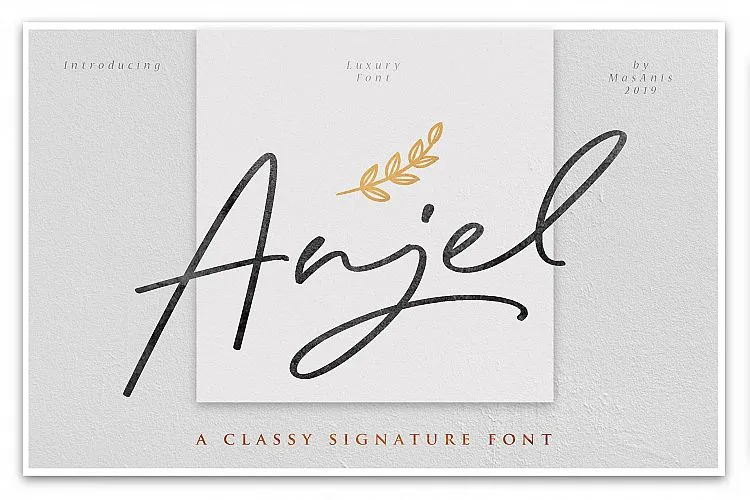
Este é um novo tipo de script autografado para anúncios de alta qualidade, com uma sensação sofisticada que certamente complementará seu próximo projeto. Introduzimos a Anjel Font. Esta foi criada e compartilhada por Mas Anis, o designer criativo do tipo de letra Anjel Signature. Este é um famoso anúncio digitado à mão cuja linguagem inclui minúsculas, maiúsculas, símbolos e suporta várias línguas. Além disso, há muitas ligaturas presentes no tipo de letra Anjel que você pode usar para criar um logo de marca, o que é útil para logotipos de anúncio ou assinatura. Também vem com um fonte swash, ideal para design gráfico de imagens de fotografias, signatários e até mesmo como uma fonte de assinatura em cartões de visitas, capas de álbuns ou qualquer projeto de design que você possa estar trabalhando. Anjel foi criado com amor para elevá-lo a um nível superior.